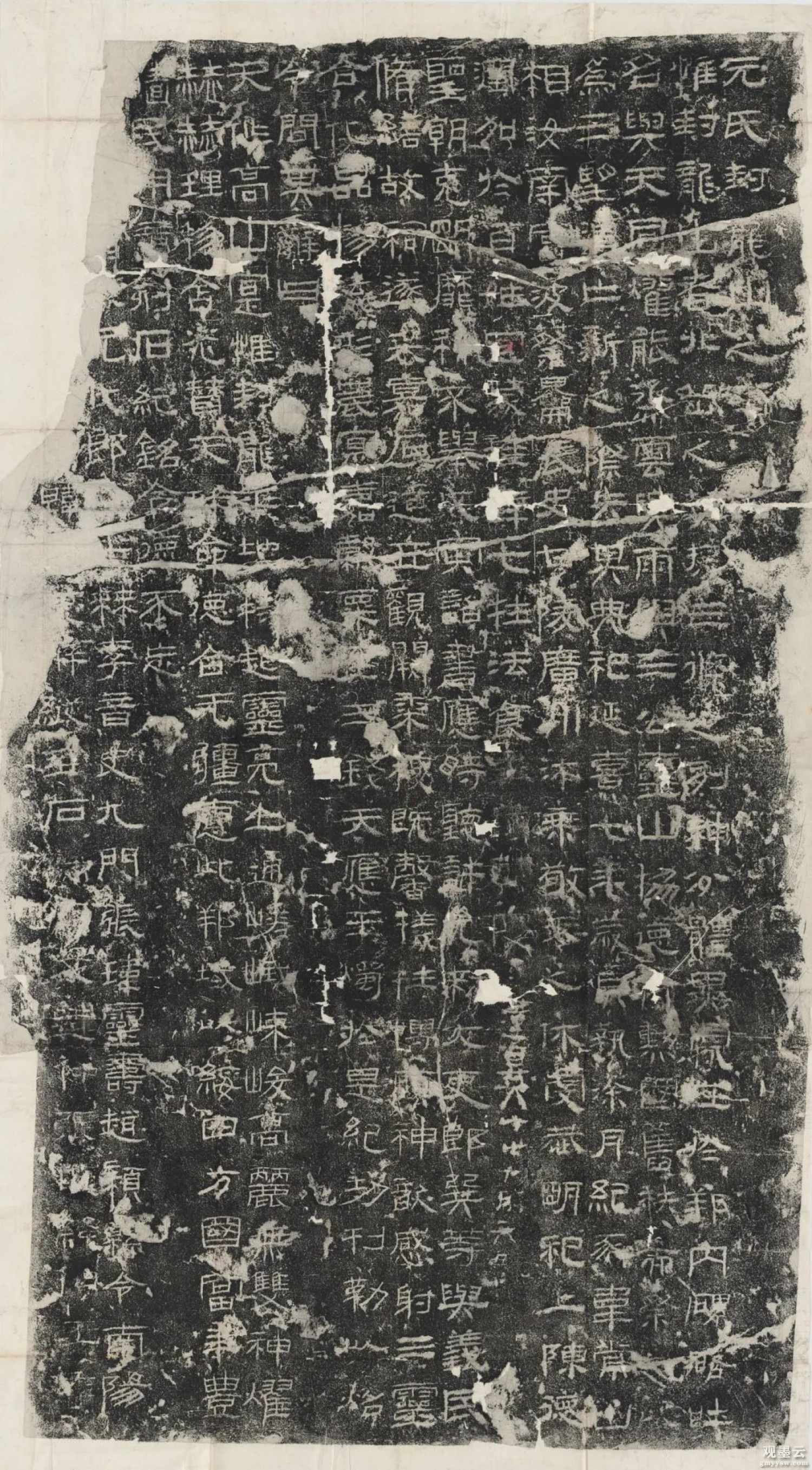
封龙山颂,全称“元氏封龙山之颂”,又称“封龙山碑”,刻于东汉延熹七年(164年)十月,原在河北元氏县王村山下,清道光二十七年(1847年)被元氏县知县刘宝楠访得,在移置城内薛文清祠时被运工裂为四块(一说三块)。至20世纪下落不明。
无额无穿,碑文15行,每行26字。记述常山相蔡爚、长史沐乘等修祠祭祀封龙山以求国富年丰之事。
《封龙山颂》虽是碑刻,但具有摩崖的气质,用笔近似《石门颂》《杨淮表记》,内敛而奔放,表现出宽博、豪放、雄肆的美感。结体也很有特色,多字形偏长,重心较高,下部时见散开,紧凑而有宽松之感,方正而有活泼之妙。章法疏朗大度,密而不挤,疏而不散,通篇分段书写,下部更显空灵。